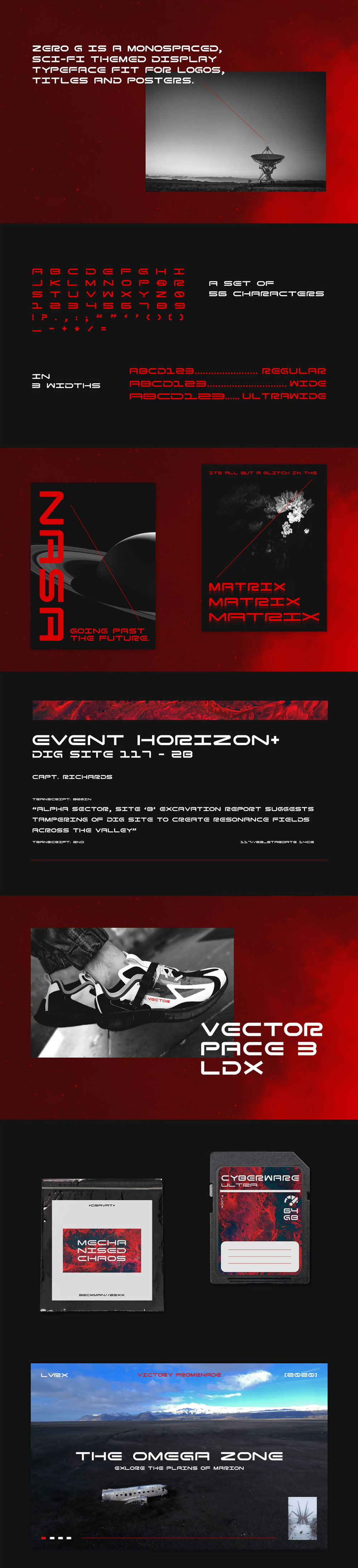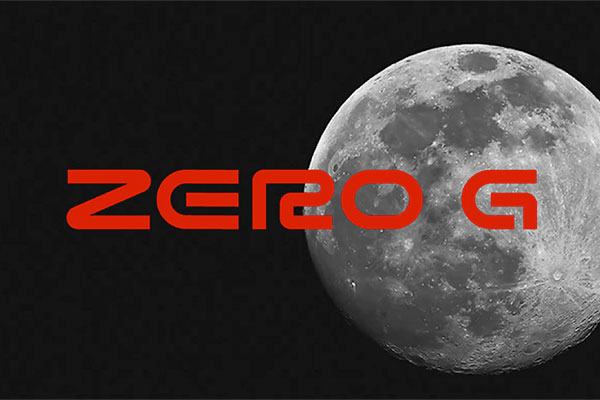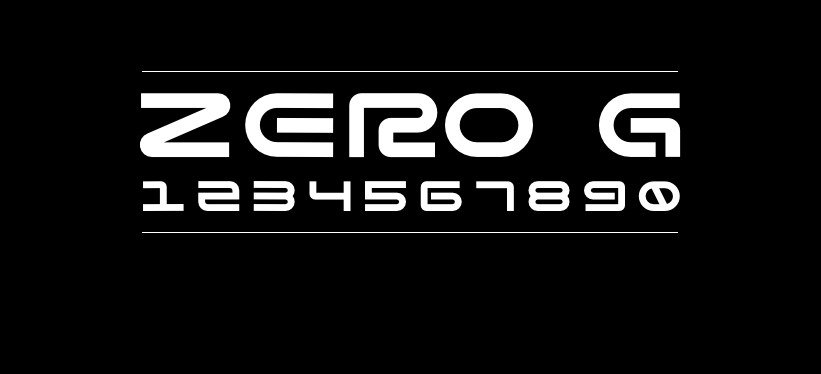
ZERO G
ZERO G字体介绍
ZERO G是印度的设计师Aromal Ashok创作的字体。这种免费的显示字体将现代性提升到一个全新的水平,字体的设计受太空旅行和未来主义的启发;Zero G包含3个字重,常适合海报和服装。ZERO G字体首发于Behance,免费供个人和商业使用。
ZERO G字体应用示例